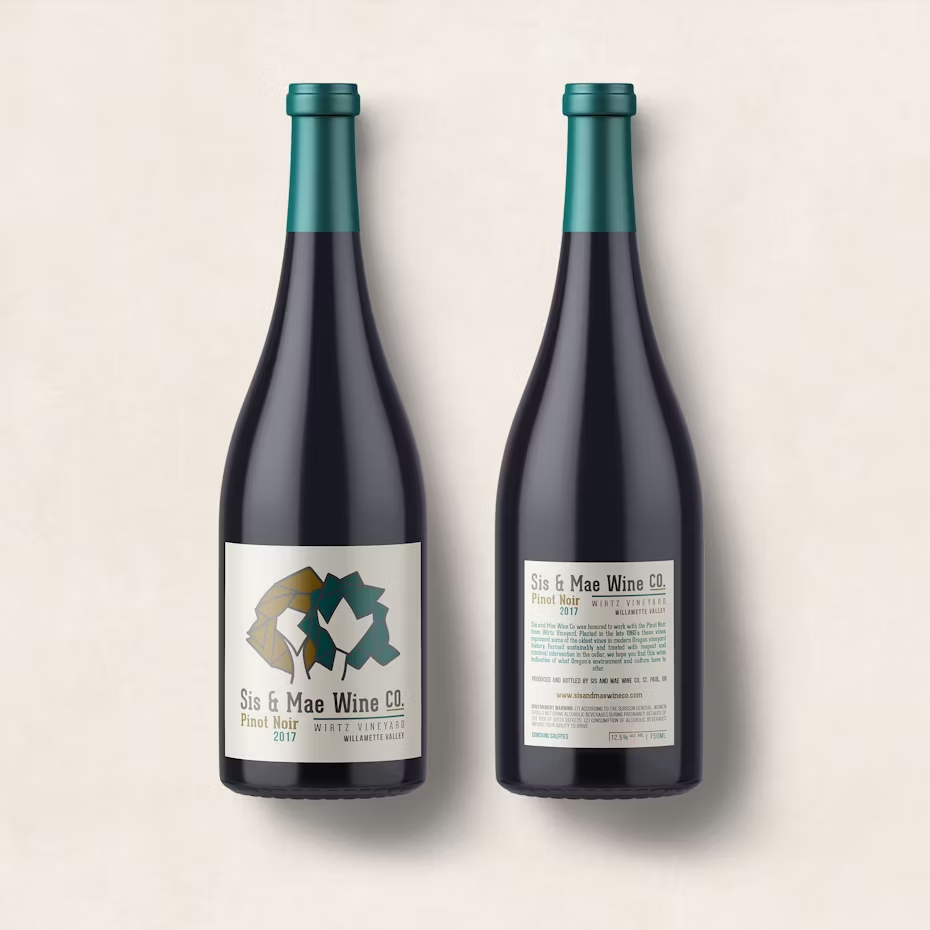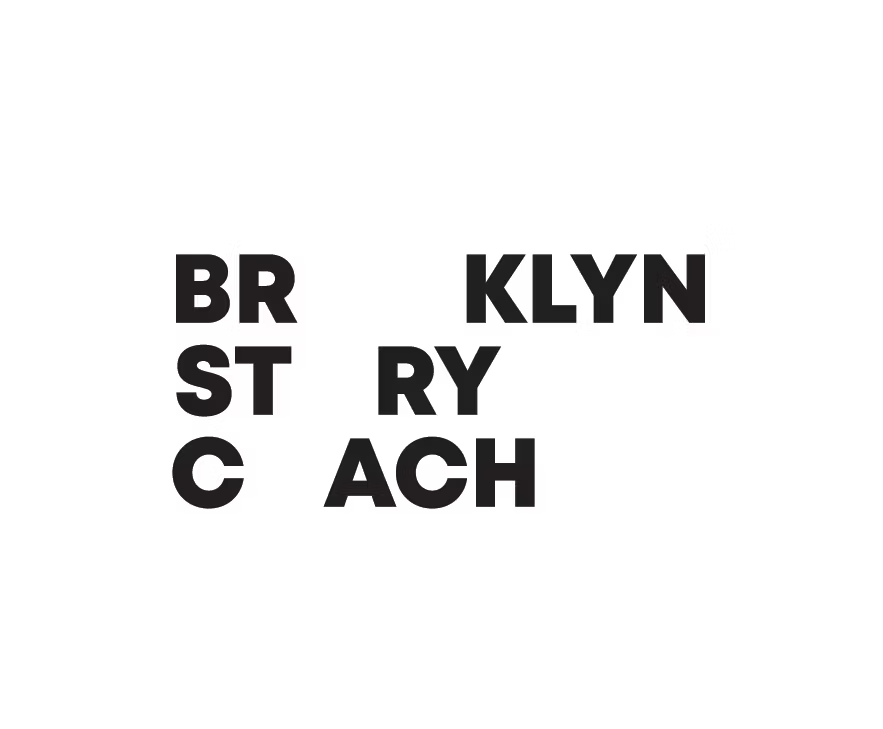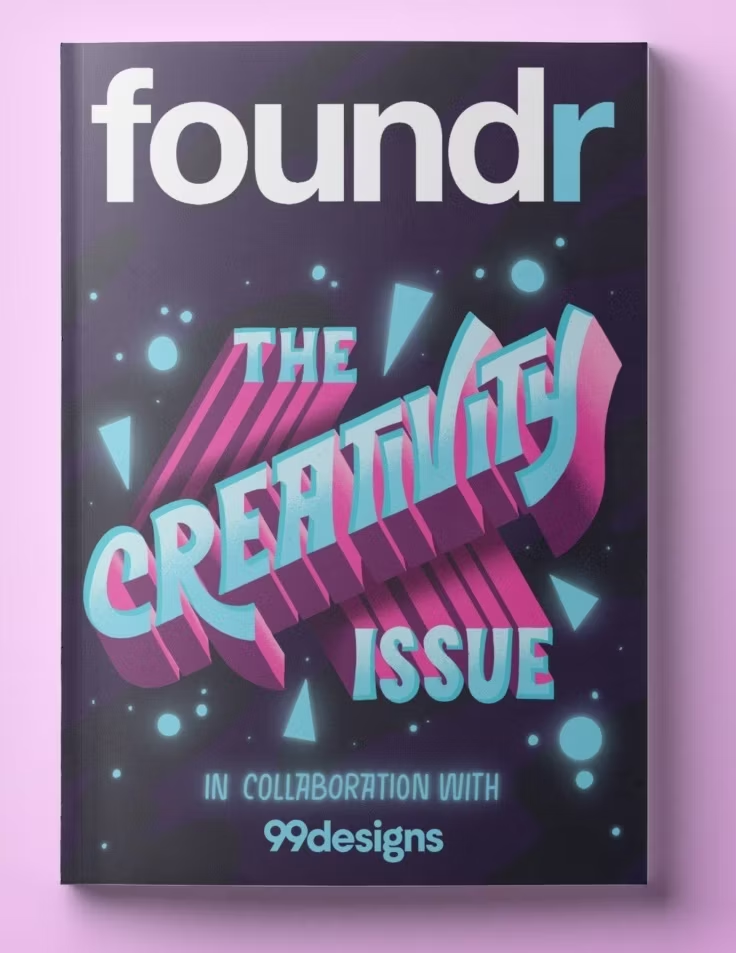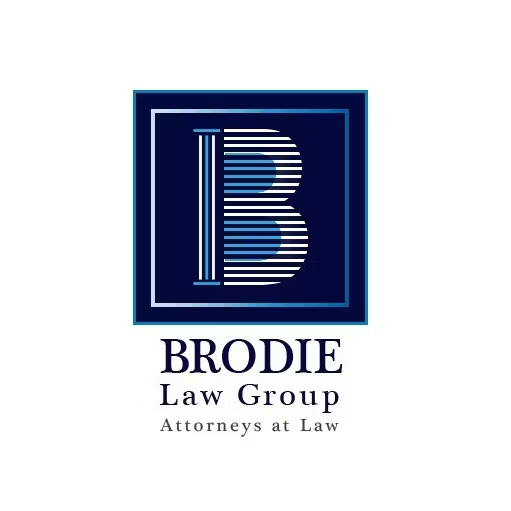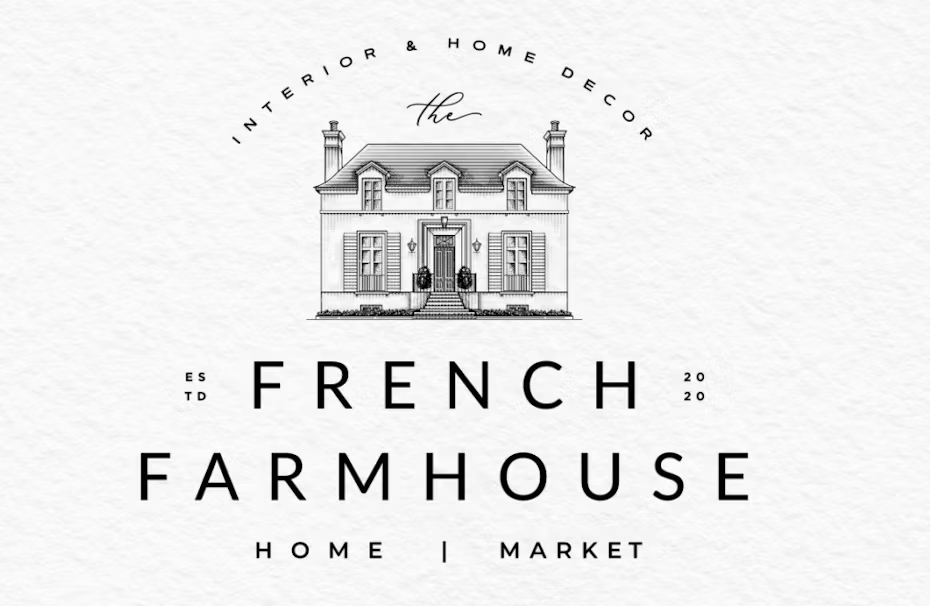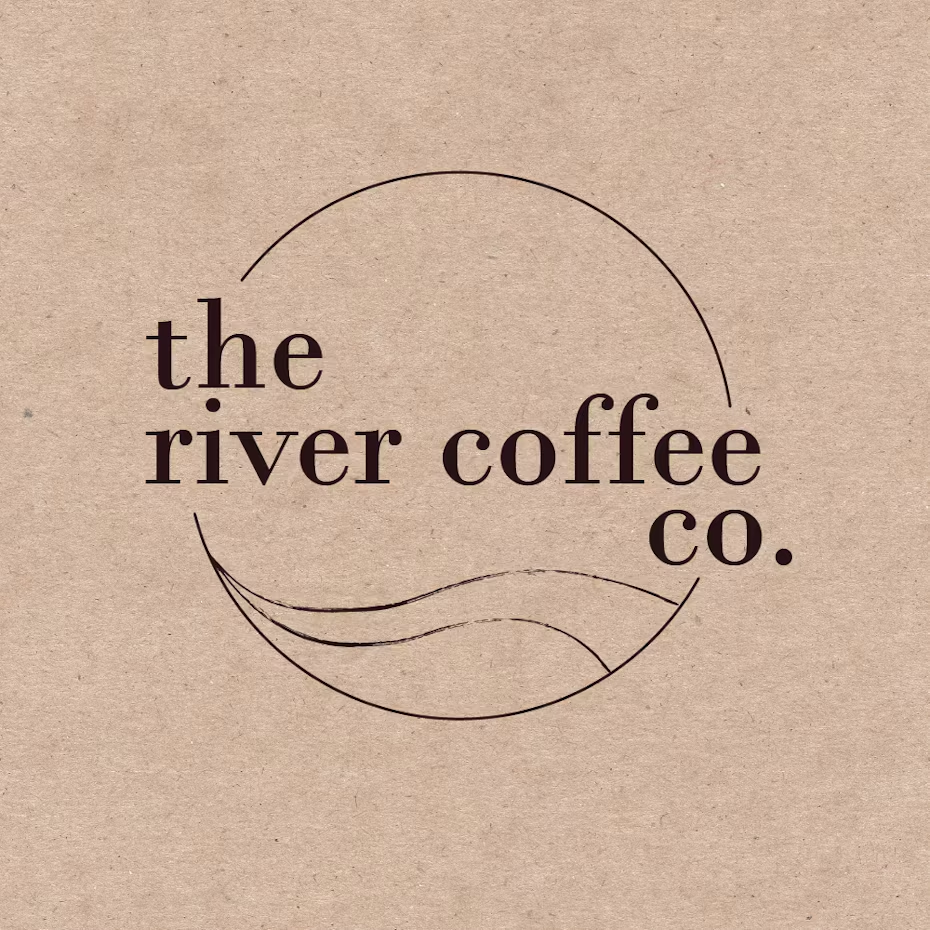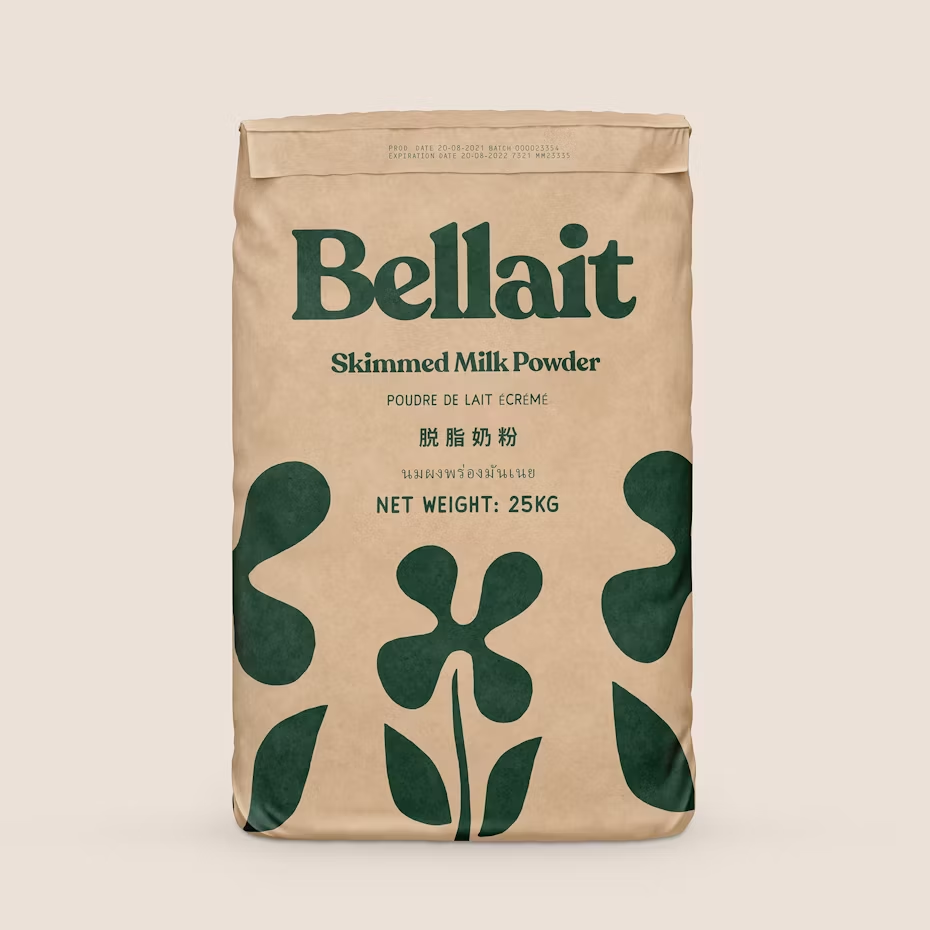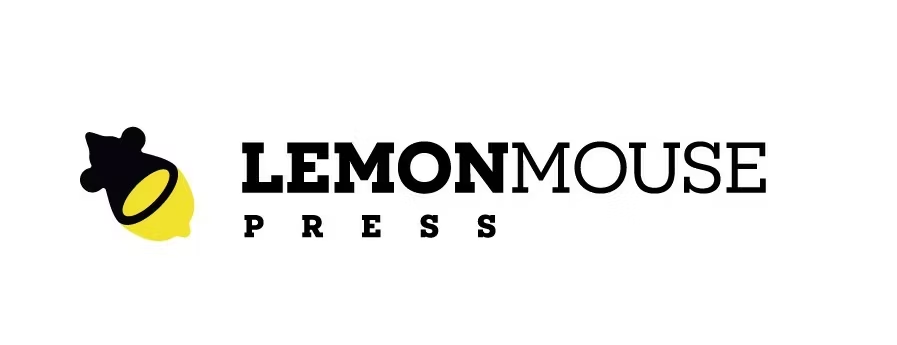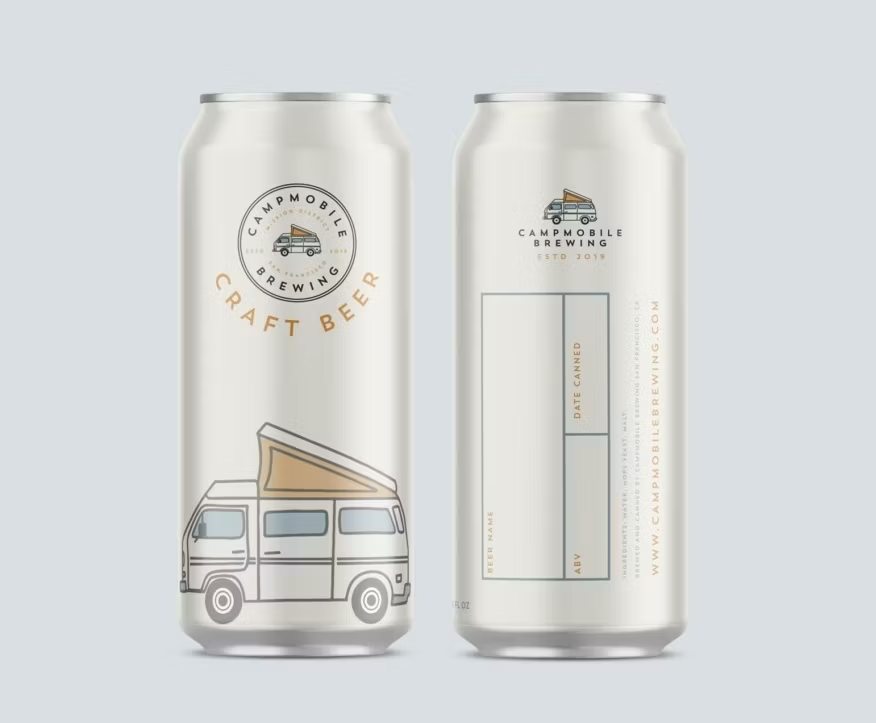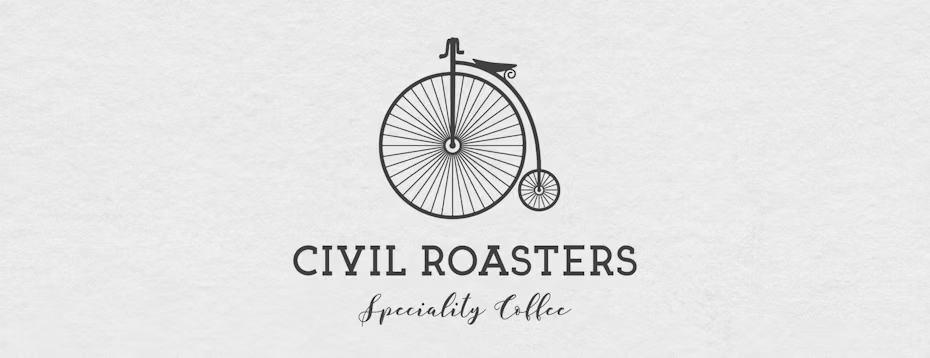
Tìm hiểu mối liên hệ giữa font chữ và cảm xúc trong thiết kế
Khi một font chữ được khai phá hết tiềm năng, nó có thể góp phần không nhỏ vào việc xây dựng hình ảnh thương hiệu trong lòng khán giả. Mỗi kiểu font đều có khả năng mang đến những xúc cảm và ấn tượng khác nhau. Trong bài viết dưới đây, hãy cùng Arena Multimedia đi sâu hơn về chủ đề thú vị này nhé!
Font chữ là một yếu tố đóng vai trò quan trọng trong thiết kế. Mỗi font chữ không chỉ là một loạt các ký tự được sắp xếp để tạo ra từng từ và câu mà còn là ngôn ngữ riêng biệt của cảm xúc. Font chữ có thể biến một văn bản bình thường thành một tác phẩm nghệ thuật, cũng có thể làm cho một trang web trở nên ấn tượng và hấp dẫn hơn.
Trong hành trình khám phá hôm nay, chúng ta sẽ đặt chân vào thế giới của font chữ – một thế giới mà không chỉ là đáp ứng được “phần nhìn” mà còn cả tâm lý và cảm xúc. Hãy cùng nhau khám phá cách mà font chữ được áp dụng như một chiến lược tâm lý để thu hút và gây ấn tượng với khán giả.
Tâm lý học font chữ là gì?
Về bản chất, tâm lý học font chữ là phản ứng trực quan và cảm xúc của bạn đối với font chữ bạn đang nhìn thấy. Theo Quy tắc Giao tiếp Cá nhân của Albert Mehrabian, 93% sự kết nối cá nhân là phi ngôn ngữ, điều này có nghĩa là những ý tưởng và giá trị cần phải được truyền đạt một cách đơn giản nhất có thể. Tùy thuộc vào những gì chúng ta đang quan sát hay suy nghĩ, cảm xúc và hành động của chúng ta sẽ bị tác động theo những cách khác nhau.
Một lý thuyết được sử dụng trong tâm lý học để giải thích cách mà một font chữ được nhận biết bởi những người khác là Mô hình Font Kolenda. Đây là một hướng dẫn từng bước phân tích cách chúng ta nhận thức về các font chữ và những gì chúng ta liên hệ từ chúng. Khi một người nhìn thấy một font chữ, họ sẽ liên kết font chữ đó với một đặc điểm. Ví dụ, nếu ai đó nhìn thấy một thương hiệu thể hình nói về việc tăng cường sức mạnh bằng font chữ đậm, khách hàng sẽ nhìn font chữ đó và tự mô tả trong đầu: dày, cồng kềnh và nặng nề. Nhận thức này sau đó cũng sẽ được liên kết với hình ảnh về thương hiệu thể hình.
Tại sao chúng ta nên sử dụng tâm lý học font chữ?
Đằng sau tâm lý học font chữ là sức mạnh thúc đẩy các quyết định. Hiểu được cách mọi người phản ứng và tương tác với font chữ có nghĩa là bạn đã nắm được cách tạo ra phản ứng mong muốn đối với đối tượng mục tiêu.
Sự kết hợp hoàn hảo giữa các font chữ cho bài đăng trên mạng xã hội giúp người tiêu dùng có nhiều khả năng tiếp tục quay lại và tương tác với nội dung của bạn hơn. Tất nhiên, điều quan trọng không kém là đảm bảo bạn không chọn sai font chữ.
Giả sử bạn đang muốn bán quà tặng trong chiến dịch Ngày của Mẹ. Bạn vừa quay một đoạn phim quảng cáo hấp dẫn hứa hẹn làm tan chảy trái tim của khán giả. Tuy nhiên, bạn sử dụng Georgia làm font chữ trong quảng cáo của mình. Thay vì cảm thấy hoài niệm, yêu thương và vui vẻ, người tiêu dùng mục tiêu của bạn sẽ có cảm giác thiết kế này có vẻ nghiêm túc và quyền lực, điều vốn không hề phù hợp với thông điệp của chiến dịch. Nếu một bánh răng hơi lỏng, toàn bộ bánh xe sẽ rời ra. Đảm bảo logo, màu sắc, hình dạng và font chữ của bạn phối hợp hài hòa với nhau là điều sẽ tạo ra sự khác biệt trong tâm lý học font chữ.